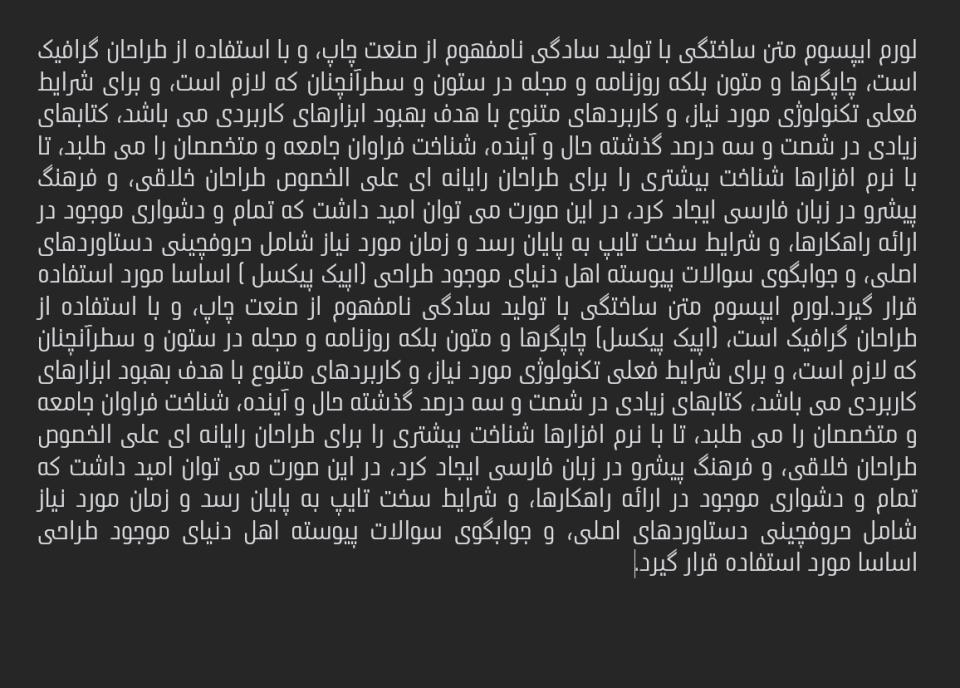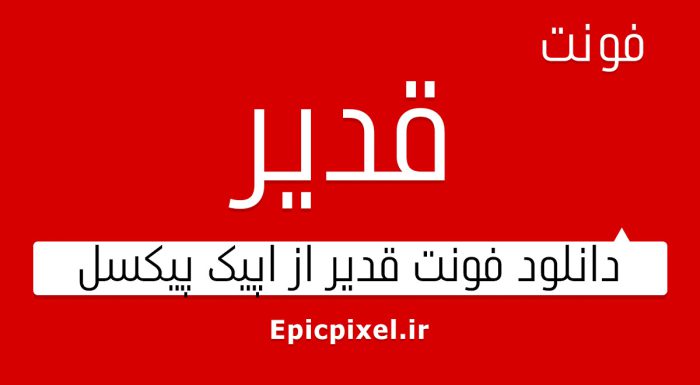
فونت غدیر فارسی، به دلیل ویژگی های خاص و منحصربه فردش، انتخابی ایده آل برای طراحی های مذهبی و سنتی به شمار می رود. این فونت با ساختار مستحکم و در عین حال ظریف خود، حس اصالت و قدمت را به مخاطب القا می کند. خطوط نرم و خوانای آن، خوانایی متن را در اندازه های مختلف تضمین می کند و در عین حال، حالتی رسمی و وزین به نوشته می بخشد.
یکی از ویژگی های برجسته فونت غدیر، هماهنگی بالای آن با زبان فارسی است. طراحی دقیق حروف و اتصالات، باعث می شود متن به صورت روان و طبیعی نمایش داده شود. این فونت، با وجود ظاهر کلاسیک خود، در طراحی های مدرن نیز قابل استفاده است و می تواند ترکیبی جذاب از سنت و مدرنیته را به وجود آورد.
البته، فونت غدیر ممکن است برای متون طولانی و با اندازه کوچک، کمی سنگین به نظر برسد. همچنین، تنوع وزن های آن محدود است و ممکن است برای برخی از پروژه ها، نیاز به فونت های مکمل باشد. با این وجود، اگر به دنبال فونتی هستید که اصالت، زیبایی و خوانایی را در کنار هم داشته باشد و به ویژه در طراحی های مرتبط با مناسبت های مذهبی مانند عید غدیر، جلوه ای خاص ایجاد کند، فونت غدیر انتخابی شایسته خواهد بود.